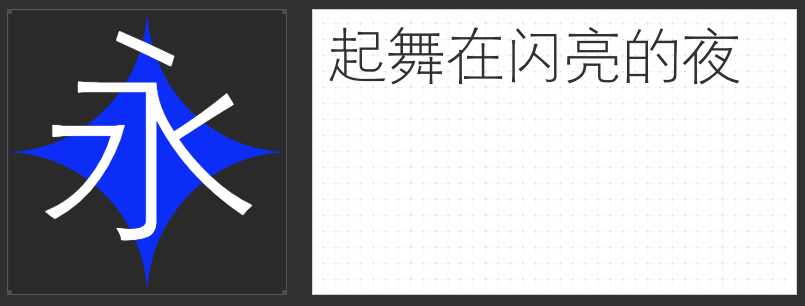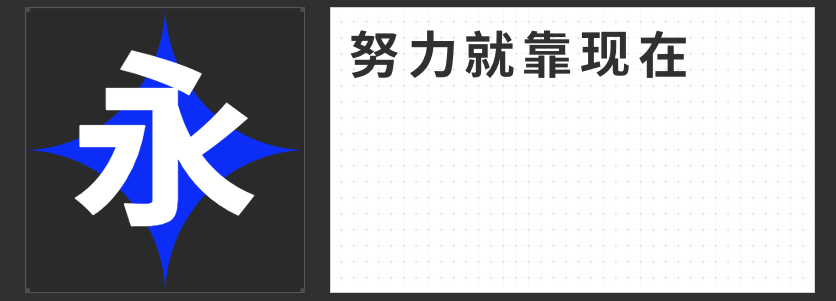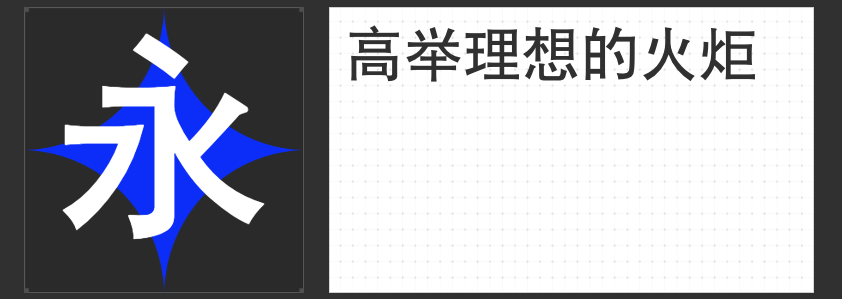
时代韵味与设计灵感的碰撞:四款精选黑体字体推荐
在设计的广阔天地里,字体不仅是信息的载体,更是情感与风格的传达者。今天,让我们一同探索四款融合了传统韵味与现代设计的黑体字体,它们各自以独特的魅力,为设计作品增添无限可能。
1.字圈也字时代黑体
这款字体是对早期铅字印刷艺术的一次致敬。随着技术的进步,它不仅保留了黑体的规矩与方正,更在笔画端口巧妙地融入了喇叭口形状的装饰,这一设计源自铅字时代为解决技术限制而创造的智慧。这种细节上的创新,使得“字圈也字时代黑体”在端庄中透露出活泼的气息,是复古与现代设计的完美融合。
2.励字综艺简繁
笔画粗壮,空间利用极致,这款字体以其独特的视觉冲击力吸引着每一位设计师的目光。圆润的拐弯处理与方正的体态相结合,既展现了力量感,又不失细腻之美。无论是简体中文还是繁体中文,都能在这款字体中找到平衡与和谐,适合需要强烈视觉效果的场景。
3.励字细黑简
清瘦纤细的线条,赋予“励字细黑简”一种高雅而精致的气质。无衬线的设计让每一笔每一划都清晰可辨,即便是在细小的文字尺寸下也能保持高度的可读性。其正方形的字面和均匀纤细的笔画,使得整体结构醒目而严密,适合追求简约而不失精致感的设计项目。
4.励字黑体简繁
当粗壮成为主旋律,“励字黑体简繁”以其超粗的笔画和稳重的字形,成为表达力量与稳定的最佳选择。没有多余的衬线装饰,字面方正,每一笔都显得那么有力而坚定。无论是标题还是正文,都能迅速抓住观众的注意力,传递出强烈的信息感。
这四款黑体字体,每一款都承载着不同的设计理念与情感表达,它们不仅是文字的呈现,更是设计灵感的源泉。选择适合项目氛围的字体,让设计作品更加生动、有力,成为连接观者与作品情感的桥梁。